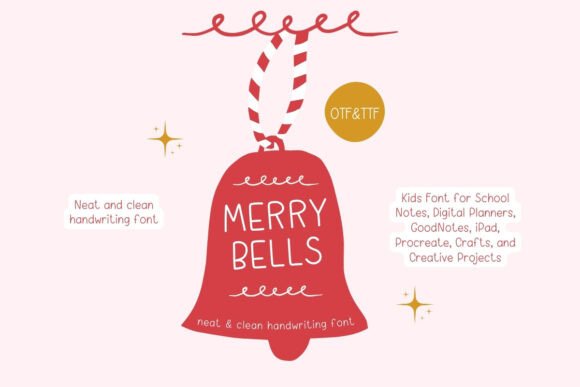
Merry Bells
Merry Bellsのような高品質の素材をお探しの場合、このプレミアムパッケージはクリエイティブなプロジェクトに素晴らしい選択です。
POD(オンデマンド印刷)製品、結婚式の招待状、またはソーシャルメディアのグラフィックを作成している場合でも、Merry Bellsは理想的です。